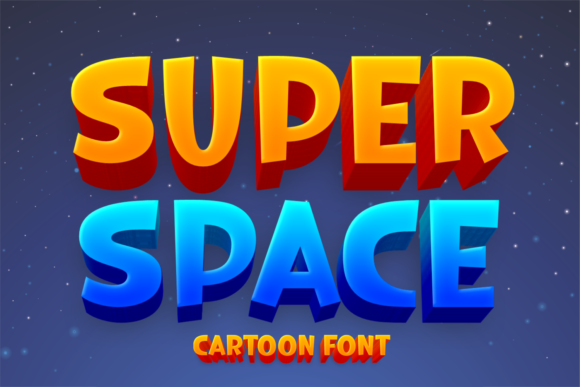
Super Space Font
Super Space Font – الخط المثالي للتصاميم المستقبلية! ????✨
أطلق العنان لإبداعك مع Super Space Font، الخط العصري المستوحى من الفضاء والتكنولوجيا المستقبلية. يتميز هذا الخط بتصميمه الأنيق والجريء، مما يجعله مثاليًا للعناوين، والشعارات، والتصميمات الرقمية، وألعاب الفيديو، والمشاريع التي تحتاج إلى لمسة من الحداثة والخيال العلمي.
???? مواصفات الخط:
✔️ تصميم عصري مستوحى من الفضاء والتكنولوجيا
✔️ حواف هندسية نظيفة لمظهر فريد
✔️ مثالي للعناوين، الشعارات، والمواد التسويقية
✔️ دعم متعدد اللغات